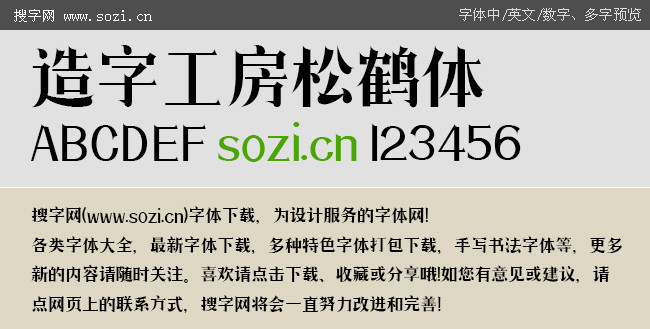
造字工房松鶴體
搜字網(wǎng)給大家提供一款造字工房松鶴體中文字體下載,造字工房松鶴體字形飽滿、整體風(fēng)格粗曠厚重,字重渾厚、棱角分明,結(jié)構(gòu)方正沉穩(wěn)不失時(shí)代氣息,橫的切角處理讓字體更顯剛毅。筆畫與筆畫間的斷層處理,使其筆畫頓挫有力、峻拔剛斷、有抑揚(yáng)頓挫之感。適用于海報(bào)設(shè)計(jì),網(wǎng)頁廣告,書籍封面,包裝設(shè)計(jì)等應(yīng)用。(本字體為個(gè)人非商用版,如需要商用請聯(lián)系官方購買版權(quán))